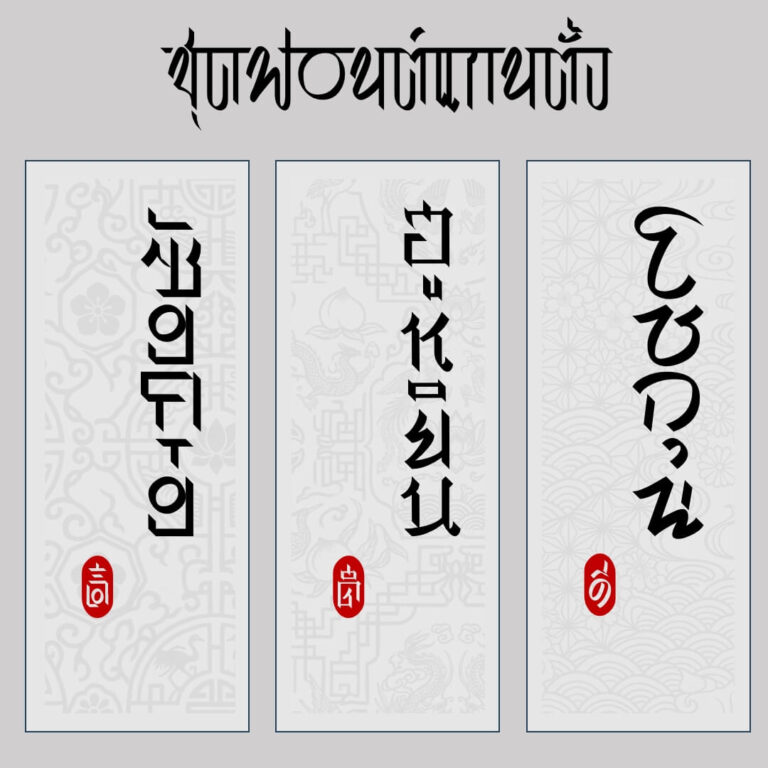
ฟอนต์ทรงสมัย ออกแบบสำหรับรูปยานยนต์ หุ่นยนต์… ตัดเส้นเชื่อม ลดเส้นโค้ง เหลือแค่ทรงเหลี่ยม ทรงกลม ประกอบกัน อ่านค่อนข้างยาก ใช้พาดหัวพอไหว… ประโยคยาวๆ อย่าได้ใช้ (เช่นเคย)
เบื้องหลังการออกแบบ : ฟอนต์ ทรงสมัย
ทรงสมัย (SOV_SongSmai)